Để có được một chiếc name card không chỉ cung cấp thông tin mà còn để lại dấu ấn khó quên, bạn cần biết cách chọn font chữ làm name card sao cho phù hợp nhất. Đây là lúc bạn cần tìm kiếm những font chữ đẹp thiết kế name card vừa có thẩm mỹ, vừa đáp ứng các yêu cầu về tính năng trên một định dạng in ấn nhỏ.
Bài viết này sẽ là cẩm nang giúp bạn làm chủ nghệ thuật lựa chọn font chữ thiết kế name card hiệu quả nhất. Hãy cùng biến chiếc name card nhỏ bé thành một công cụ marketing cá nhân mạnh mẽ!
Gợi ý các Font chữ thiết kế Name Card phổ biến
Dưới đây là một số gợi ý font được các nhà thiết kế và doanh nghiệp ưa chuộng vì tính thẩm mỹ, sự chuyên nghiệp và khả năng dễ đọc tốt trên name card.
Các Font Sans-serif Được Ưu Tiên (Hiện đại, Rõ ràng):
- Open Sans: Rất linh hoạt, thân thiện, dễ đọc ở mọi kích thước. Phù hợp cho cả tên và thông tin liên hệ. (Miễn phí trên Google Fonts)
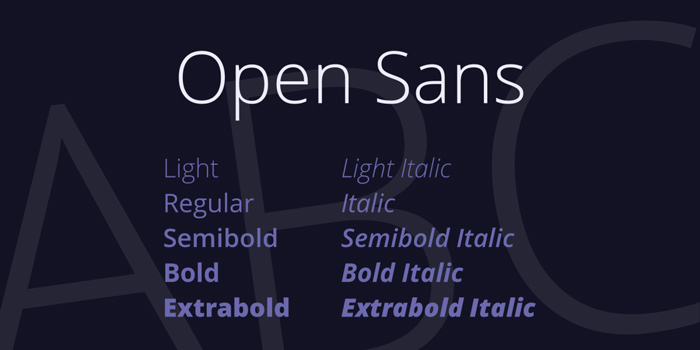
- Roboto: Hiện đại, hình học, sạch sẽ. Rõ ràng và chuyên nghiệp, lý tưởng cho name card cần vẻ ngoài hiện đại, tối giản. (Miễn phí trên Google Fonts)
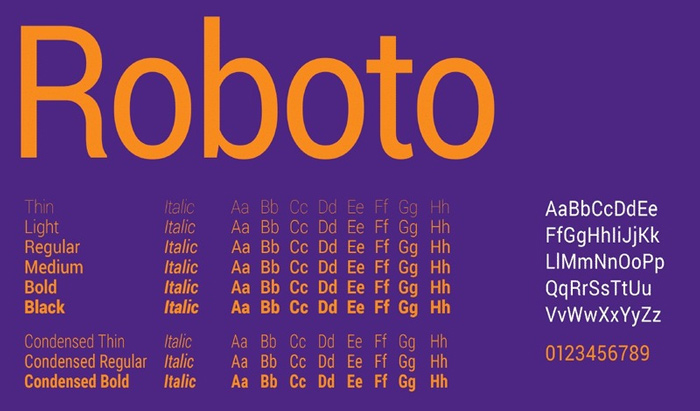
- Lato: Cân bằng, dễ đọc, mang lại cảm giác vừa chuyên nghiệp vừa dễ gần. (Miễn phí trên Google Fonts)
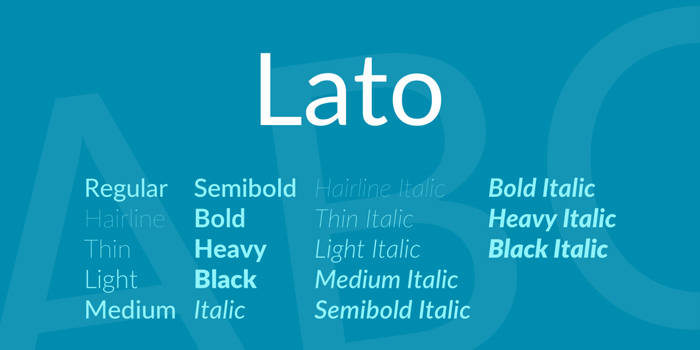
- Montserrat: Mạnh mẽ, hình học, nhiều độ đậm. Phiên bản Light/Regular cho thông tin chi tiết, phiên bản Medium/Bold cho tên/công ty. (Miễn phí trên Google Fonts)
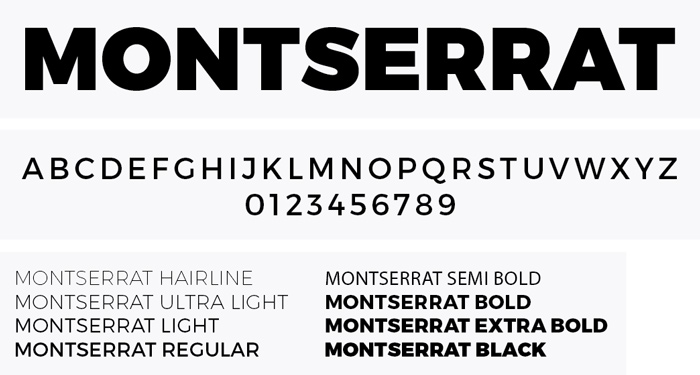
- Arial / Calibri: Các font hệ thống quen thuộc, an toàn, luôn in rõ ràng. Lựa chọn cơ bản và đáng tin cậy.
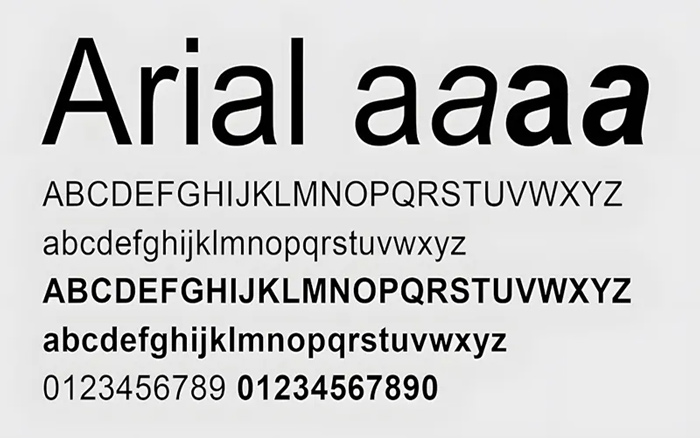
Các Font Serif Được Ưu Tiên (Cổ điển, Sang trọng)
- Georgia: Một font Serif truyền thống, dễ đọc ở cỡ nhỏ. Mang lại vẻ đáng tin cậy, cổ điển. (Thường có sẵn trên hệ điều hành)
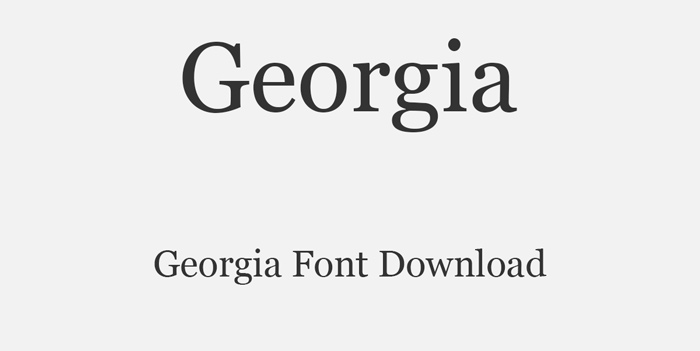
- Palatino / Palatino Linotype: Sang trọng, thanh lịch, rõ ràng. Thích hợp cho name card cần nét tinh tế, cổ điển. (Thường có sẵn trên hệ điều hành)
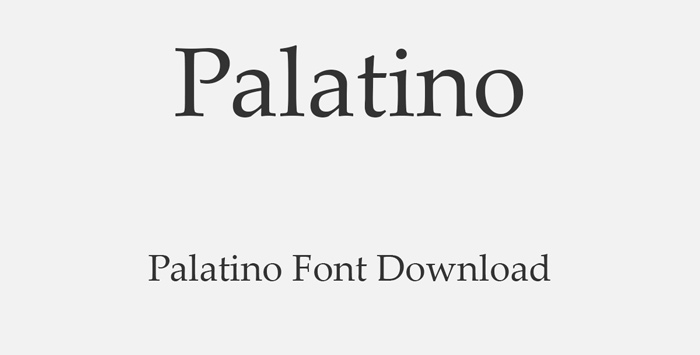
- Merriweather: Thiết kế tối ưu cho màn hình nhưng in rất tốt, có nét thân thiện nhưng vẫn trang trọng. (Miễn phí trên Google Fonts)
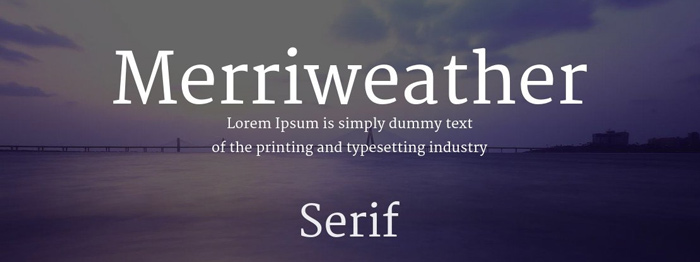
Các Font Tạo Điểm Nhấn (Chỉ dùng cho TÊN hoặc Tên Công ty)
- Playfair Display (Serif Display): Sang trọng, có nét tương phản cao. Có thể dùng cho tên để tạo sự nổi bật, kịch tính (nếu phù hợp phong cách). (Miễn phí trên Google Fonts)
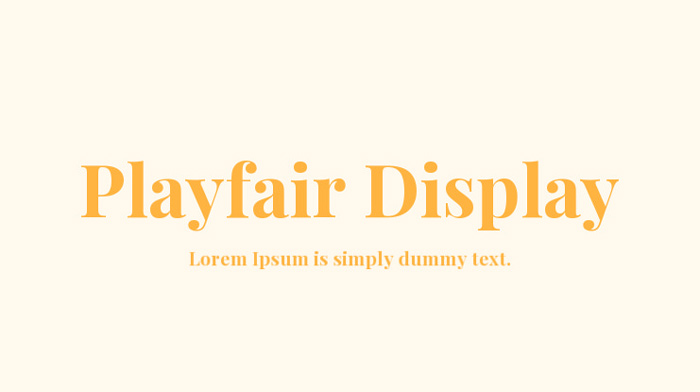
Vai trò của Font chữ trên Name Card
Trên một chiếc name card nhỏ gọn, font chữ đẹp thiết kế name card không chỉ là chi tiết trang trí. Nó đóng vai trò cốt lõi, quyết định hiệu quả của công cụ kết nối này:
- Tạo Ấn Tượng Đầu Tiên Mạnh Mẽ: Name card là cơ hội để bạn gây ấn tượng ngay từ lần gặp đầu. Font chữ góp phần định hình cảm nhận ban đầu (chuyên nghiệp, sáng tạo, sang trọng...), làm cho chiếc card và người trao nó trở nên đáng nhớ hơn. Đây là cách tạo ấn tượng đầu tiên name card.
- Thể hiện Chuyên nghiệp và Bản sắc: Lựa chọn font chữ phản ánh phong cách và giá trị của cá nhân hoặc thương hiệu bạn. Một font chữ chuyên nghiệp name card phù hợp sẽ củng cố hình ảnh và xây dựng bộ mặt thương hiệu name card.
- Đảm bảo Dễ đọc ở Kích thước Nhỏ: Quan trọng nhất! Thông tin liên hệ (số điện thoại, email...) phải font chữ dễ đọc name card trên không gian hạn chế của name card. Kích thước font name card và thiết kế font cần đảm bảo sự rõ ràng tối đa.
Đặc điểm Font chữ thiết kế Name Card đẹp
Bạn cần tìm kiếm những font sở hữu các đặc điểm font name card được tối ưu cho định dạng nhỏ và mục đích tạo ấn tượng.
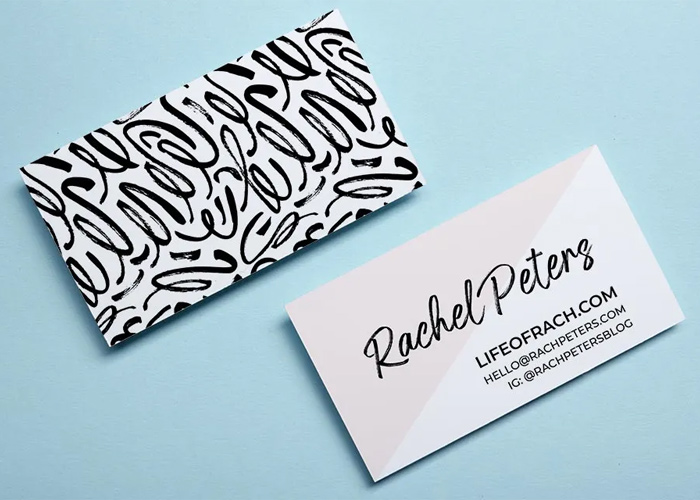
- Dễ Đọc Ở Kích thước Nhỏ: Điều quan trọng nhất. Font phải rõ ràng, dễ đọc ngay cả khi in ở kích thước font name card nhỏ (thường là 7-9pt cho thông tin liên hệ). Đây chính là tiêu chí hàng đầu của font chữ dễ đọc name card.
- Phù hợp Phong cách & Thương hiệu: Font chữ cần phản ánh đúng hình ảnh (hiện đại, cổ điển, sáng tạo...) và giá trị mà bạn hoặc thương hiệu muốn truyền tải. Font cần phù hợp thương hiệu name card để tạo nên font name card đẹp đúng nghĩa.
- Thiết kế Sạch Sẽ, Rõ ràng: Tránh font quá mảnh, quá nhiều chi tiết hoặc phức tạp. Font có hình dáng sạch, rõ ràng, không bị bết khi in nhỏ sẽ chuyên nghiệp hơn. Hãy tìm font đơn giản name card.
- Có Biến thể Độ Đậm: Font nên có ít nhất 2 độ đậm khác nhau (ví dụ: thường và đậm) để bạn tạo sự nổi bật cho tên so với thông tin chi tiết mà không cần dùng nhiều loại font khác nhau.
Nguyên tắc chọn Font chữ thiết kế Name Card
Áp dụng những nguyên tắc cốt lõi sau để có name card hiệu quả:
- Ưu tiên Dễ Đọc: Mọi thứ trên name card phải dễ đọc nhanh. Font chữ, kích thước font name card, và khoảng cách đều phải phục vụ mục tiêu này. Đảm bảo font chữ dễ đọc name card.
- Chọn Cỡ chữ Phù hợp: Tên và thông tin chính (công ty) lớn hơn. Thông tin liên hệ (SĐT, Email...) nhỏ hơn (thường 7-9pt), nhưng phải đảm bảo đọc được rõ ràng.
- Chú ý Khoảng cách: Đảm bảo khoảng cách chữ name card và khoảng cách dòng đủ thoáng để văn bản không bị dính vào nhau hoặc rời rạc, giúp dễ quét mắt.
- Phối font Đơn giản: Chỉ dùng 1-2 loại font. Nếu phối, chúng cần hài hòa và giúp phân biệt các phần thông tin (tên và chi tiết liên hệ).
- Kiểm tra In ấn: Luôn in thử trên chất liệu name card thật để xem font chữ có in ra rõ ràng như trên màn hình không.
Những sai lầm cốt lõi khi chọn Font thiết kế Name Card
Để có chiếc name card hiệu quả, hãy tránh những sai lầm khi chọn font chữ thiết kế, in ấn name card sau đây:
- Font Khó Đọc Hoặc Quá Nhỏ: Lỗi nghiêm trọng nhất. Font quá mảnh, cầu kỳ, hoặc kích thước font name card sai khiến thông tin liên hệ vô dụng. Đảm bảo font chữ dễ đọc name card.
- Dùng Quá Nhiều Font Hoặc Phối Không Hài Hòa: Nhiều hơn 2 loại font làm card lộn xộn, thiếu chuyên nghiệp.
- Khoảng Cách Chữ: Chữ hoặc dòng dính vào nhau/quá xa làm khó đọc, kém chuyên nghiệp.
- Font Không Hợp Phong Cách: Font không phản ánh đúng hình ảnh cá nhân/thương hiệu (ví dụ: font trẻ con cho công ty nghiêm túc).
- Không Có Bản Quyền Font: Dùng font trả phí trái phép là rủi ro pháp lý.
- Không In Thử: Chỉ nhìn trên màn hình. In thử trên giấy name card là bắt buộc để kiểm tra độ rõ ràng thật sự.
Để làm cho name card của bạn nổi bật và tạo ấn tượng mạnh mẽ ngay từ cái nhìn đầu tiên, chúng tôi cung cấp dịch vụ thiết kế name card chuyên nghiệp. Chúng tôi sẽ giúp bạn có được những tấm name card độc đáo, thể hiện phong cách riêng và nâng tầm thương hiệu cá nhân hoặc doanh nghiệp.
Qua các phần đã tìm hiểu, chúng ta thấy rằng font chữ đẹp thiết kế name card không chỉ đơn giản là chọn một kiểu chữ "ưng mắt". Đó là quyết định chiến lược, là yếu tố then chốt giúp name card của bạn tạo được ấn tượng đầu tiên name card mạnh mẽ, thể hiện tính chuyên nghiệp và đảm bảo thông tin liên hệ được truyền tải rõ ràng trên một không gian rất hạn chế.